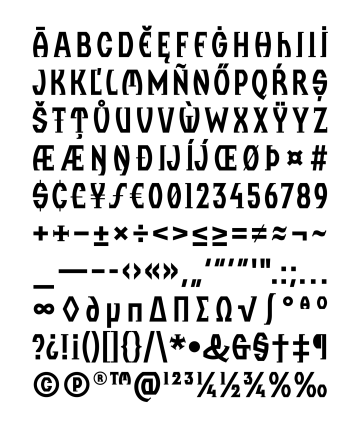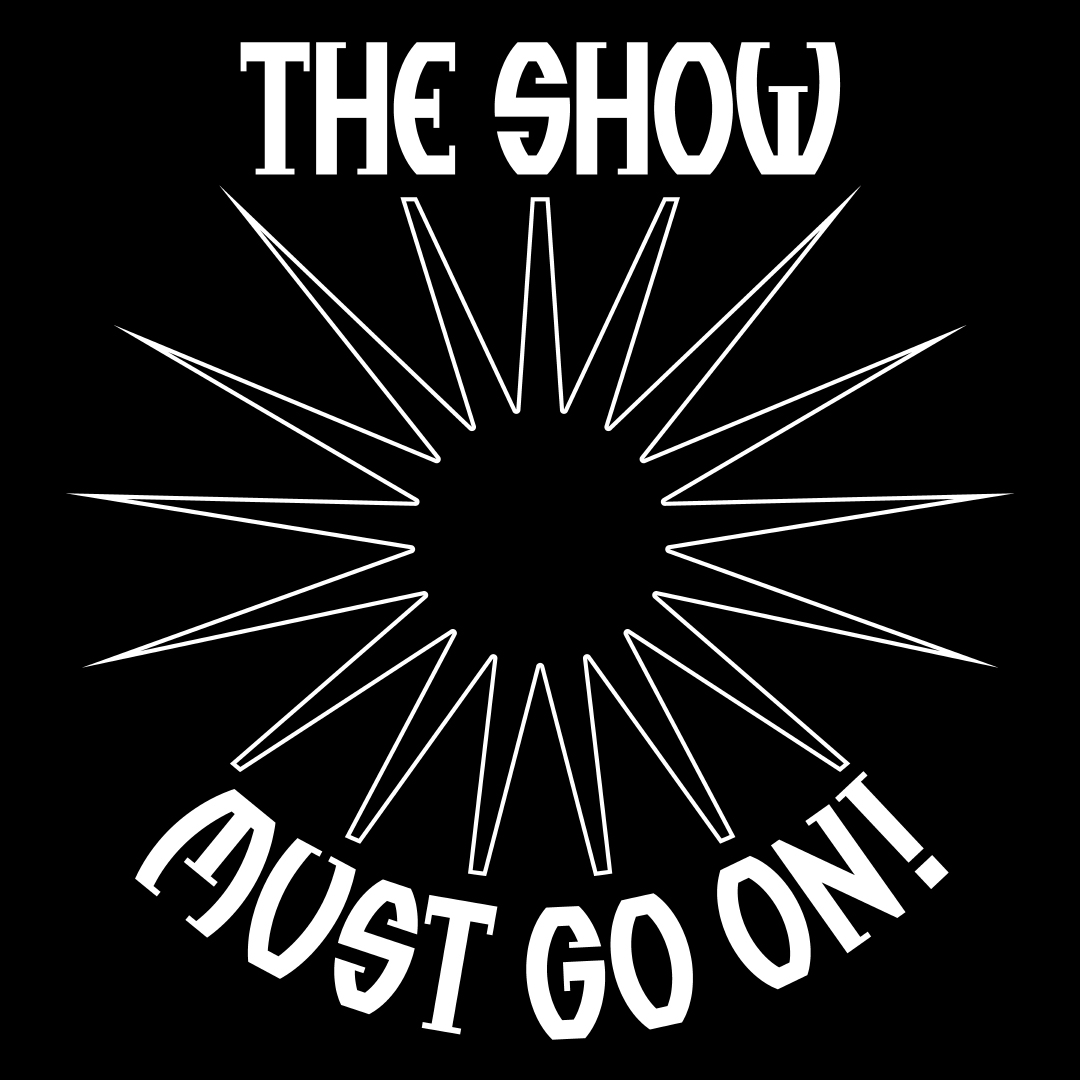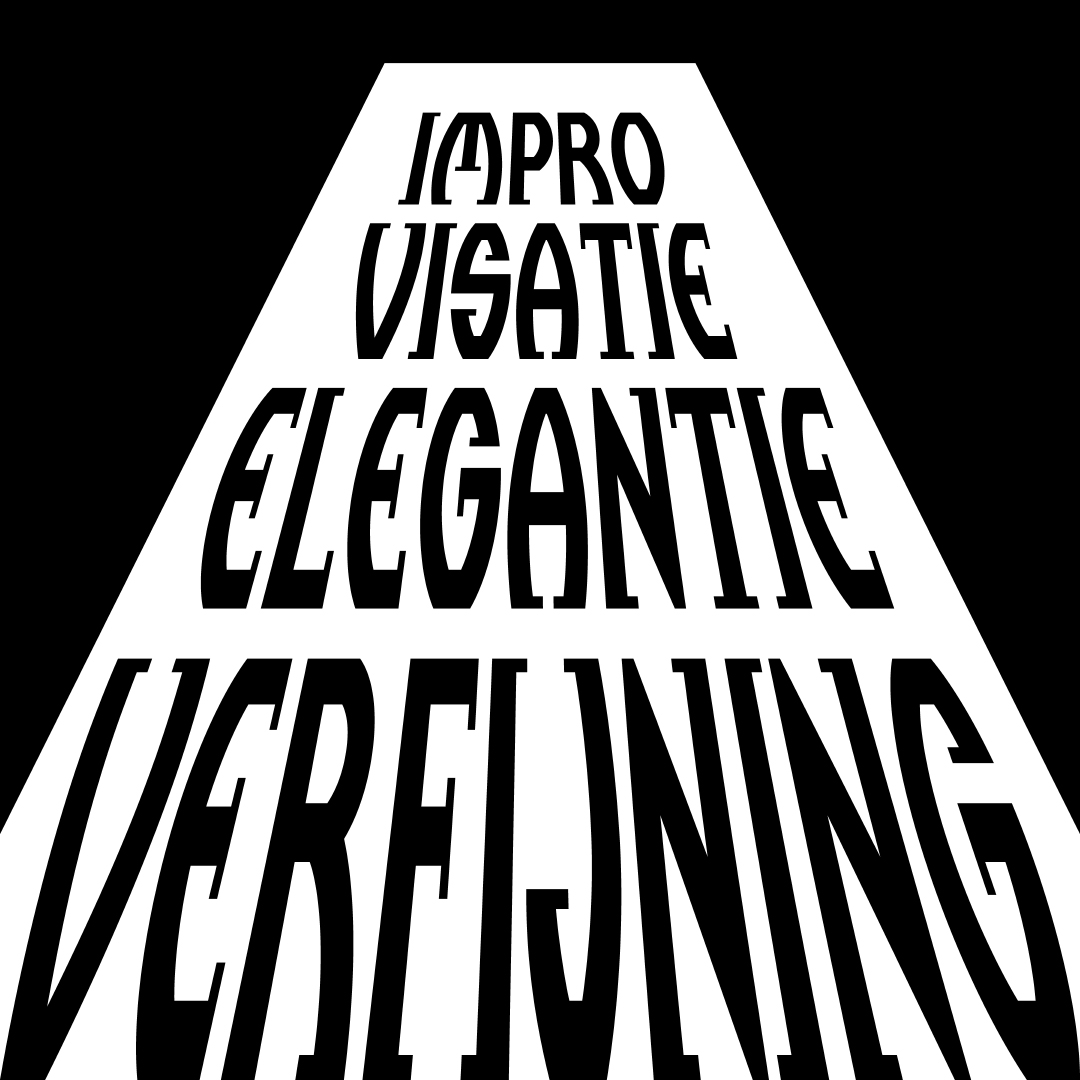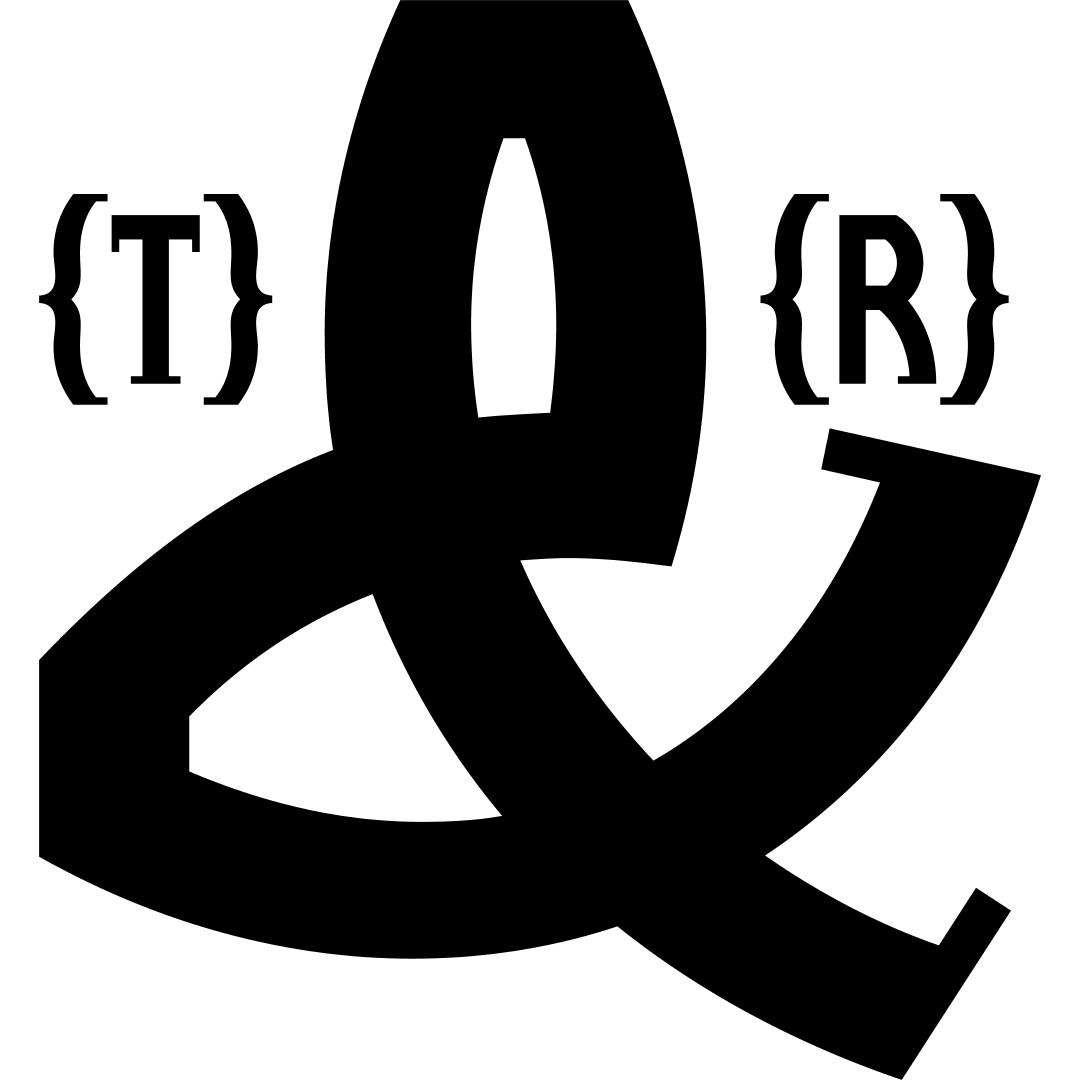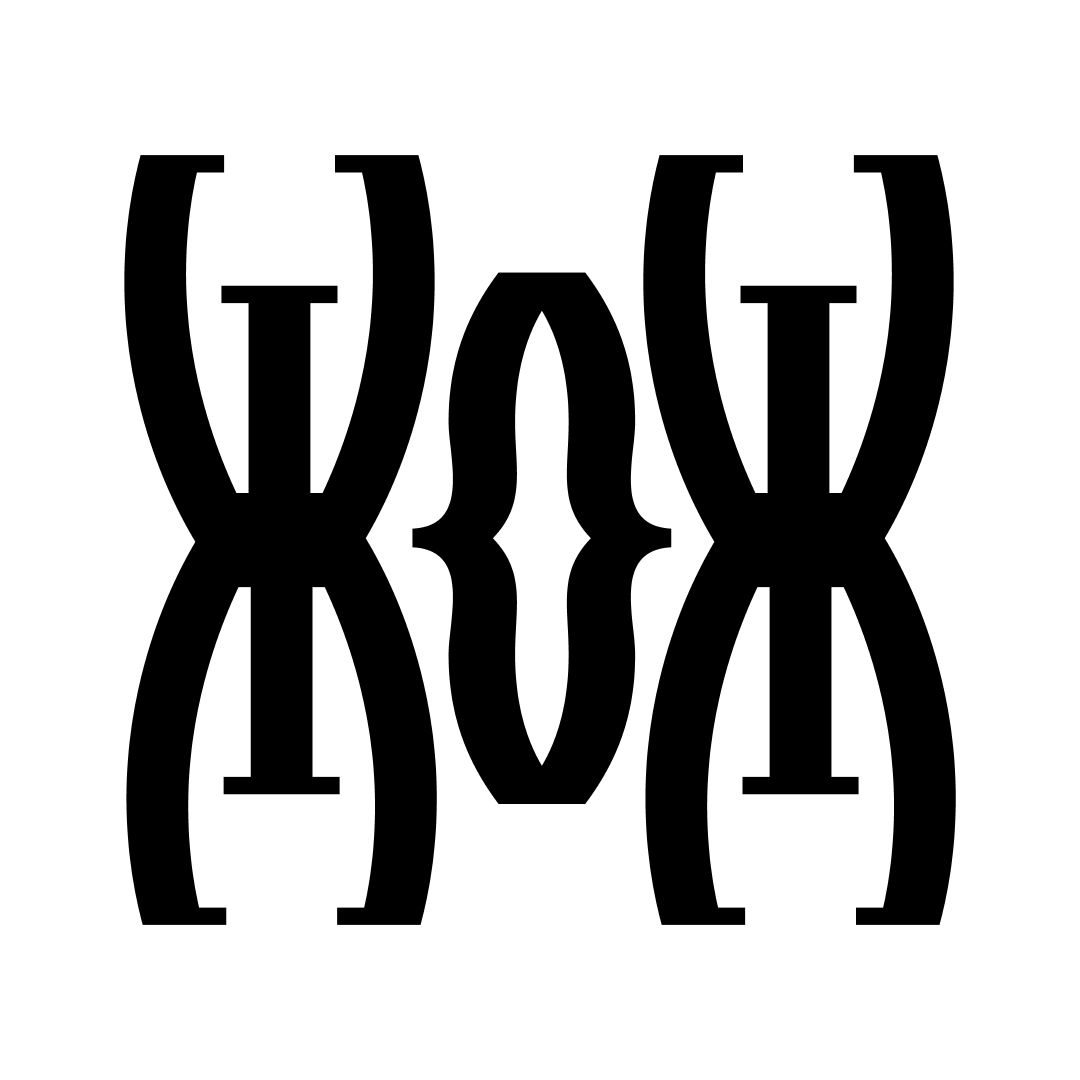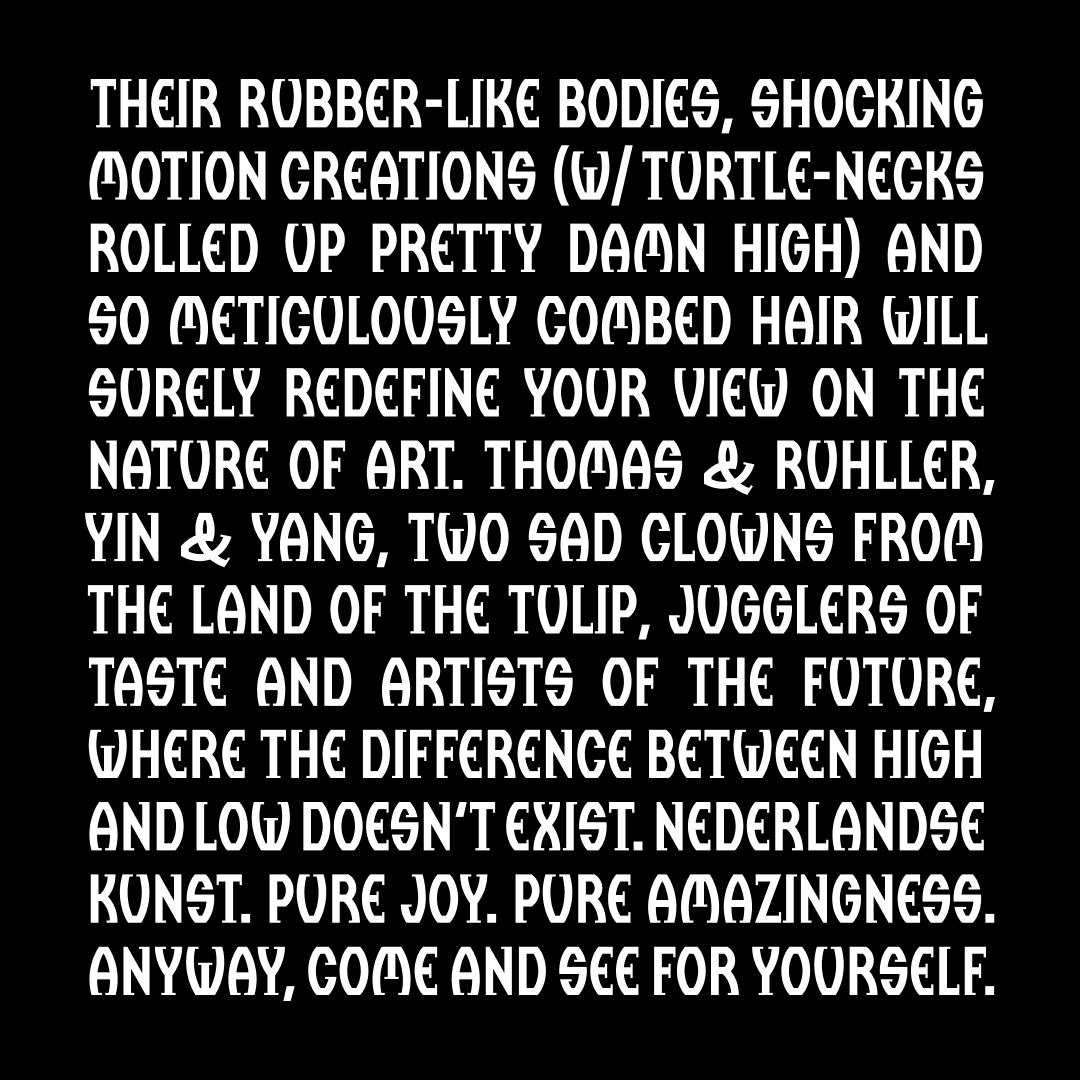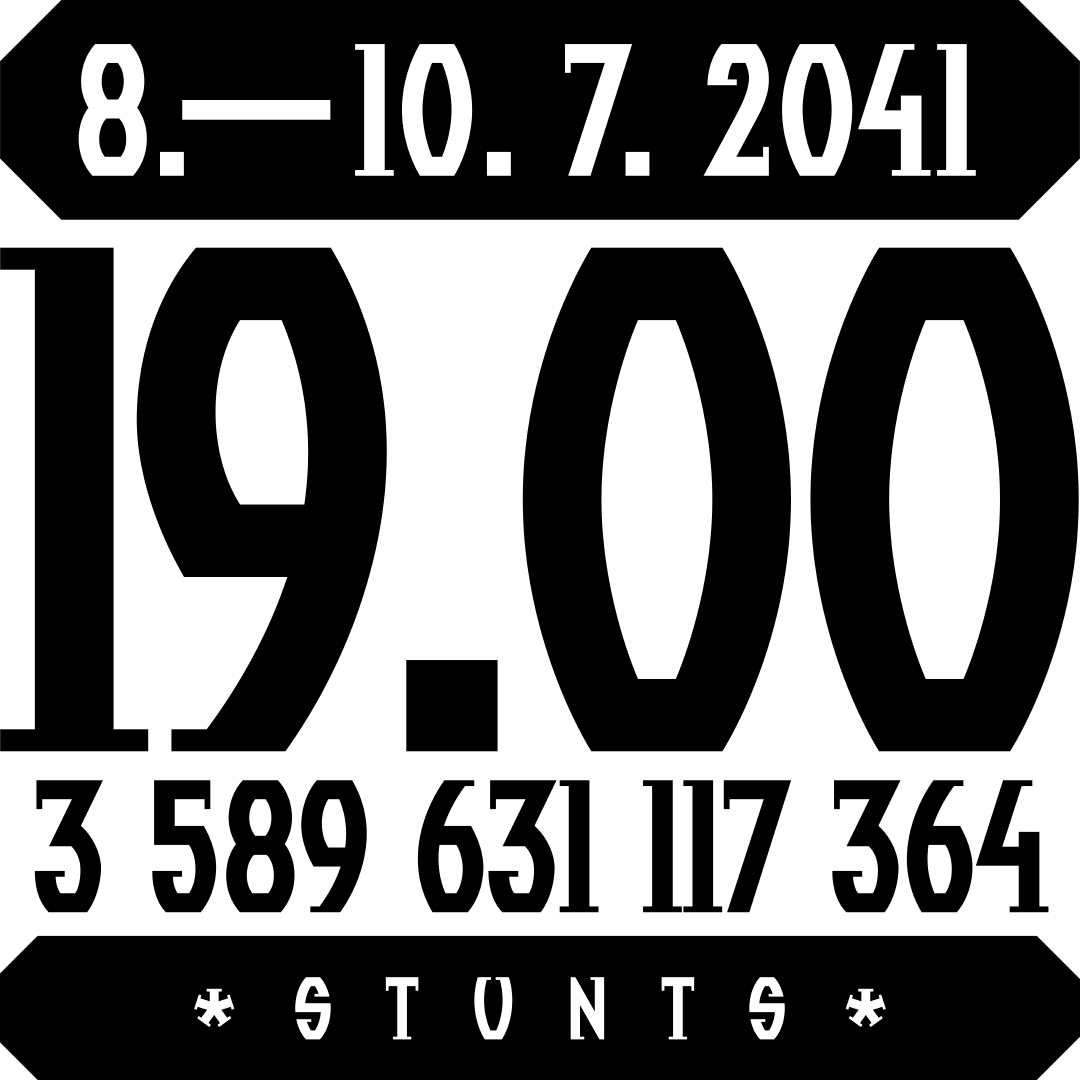
Thomas Ruhller
V předdigitálních 80. letech navrhovat plakát znamenalo pro Aleše Najbrta navrhovat na něj vlastní písma. Z některých zůstalo právě jen několik liter potřebných k jménu filmu nebo přestavení, ale na plakátě Thomase & Ruhllera už bylo tolik textu, že dávalo smysl dokončit celou abecedu. Thomas & Ruhller, „performance parodující performance“, z níž se během let stala performance regulérní, od začátku na podporu mystifikace o holandských ekvilibristech vyžadovala profesionálně působící promo a množství (pseudoholandských) nápisů. Písmo, které k tomu účelu vzniklo, následuje vytáhlé tvary samotných pomalu se pohybujících performerů (Aleš Najbrt & Jan Slovák), s ostrými zakončeními polovičních patek adekvátními své postmoderní době. Písmo je víc než tři desetiletí základem grafické identity minimalistické dvojice, ale krom očekávatelných míst jako je časopis Reflex v dobách Najbrtovy artdirekce, došlo použití na tak různých místech jako je výstava umělce Federica Díaze nebo album skutečně mezinárodně proslulého hráče na lesní roh Radka Baboráka. V roce 2013 Najbrt písmo digitalizoval s pomocí Tomáše Brousila a Radka Siduna, kteří přidali vlastní alternativní znaky a doplnili znakovou sadu pro většinu latinkového světa. Verzálková abeceda ale dál nabízí jen jedinou minusku „h“ coby západní akcent pro světoznámá jména Thomas & Ruhller.
Designer: Aleš Najbrt